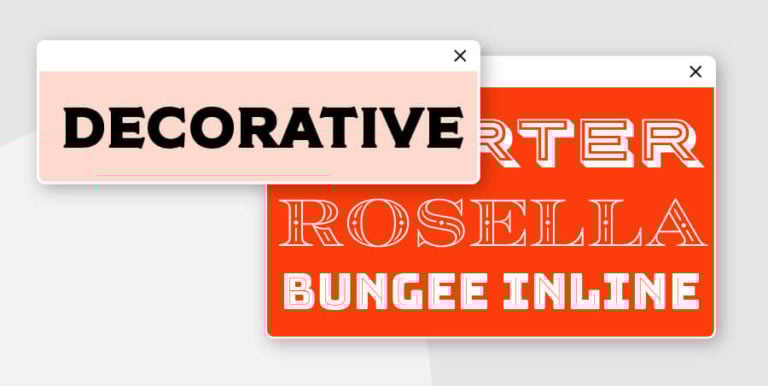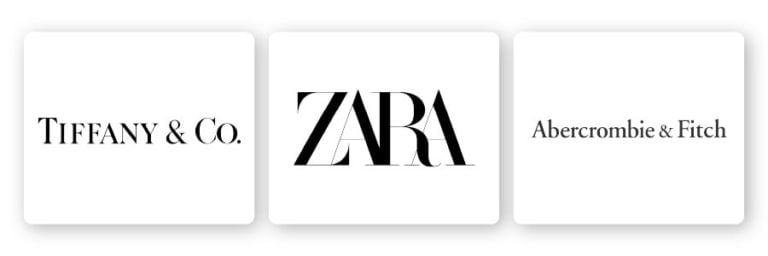
Wenn Sie ein Logo entwerfen wollen, ist die Wahl der richtigen Schriftart vergleichbar mit der Auswahl der Außenfarbe für Ihr Haus. Sie sollten genau die richtige aussuchen, denn das neue Erscheinungsbild gibt Ihrem Zuhause neue Frische und sagt Ihren Gästen viel über die Menschen, die darin wohnen. Abblätternde Farbe zeugt von einem vernachlässigtem Zuhause; glänzende, lebendige Farben besagt, dass es sich um ein gut gepflegtes Heim handelt.
In der Weise, wie Farben Aussagen über Häuser machen, so werden Schriftarten dazu benutzt, um spezifische Reaktionen hervorzurufen und einzigartige gedankliche Assoziationen mit einer Marke herzustellen. Jede Schriftart hat ihre eigenen Vor- und Nachteile sowie psychologische Bedeutung.
Heutzutage sind Tausende von kostenlosen Schriftarten verfügbar, aber die meisten lassen sich in fünf weite Kategorien aufteilen. Jeder dieser Stile besitzt charakteristische Merkmale und wie der jeweilige eingesetzt bzw. gestaltet wird, spielt eine wichtige Rolle für dessen symbolische Bedeutung – was sich wiederum auf Ihr endgültiges Logodesign auswirkt.
Lesen Sie weiter, um mehr über jede Schriftart zu erfahren, und finden Sie heraus, welcher Stil die richtige Auswirkung auf Ihr Logo hat.
Die verschiedenen Typen von Schriftarten, und wann man sie verwendet
Serifen-Fonts
Dies sind die ältesten Schriftarten, von denen die ersten Beispiele bereits im späten 15. Jahrhundert auftauchen. Das Wort „Serife“ bezieht sich auf die kleinen Füße, mit denen die einzelnen Buchstaben oben und unten ausgestattet sind. Diese winzigen Verzierungen sind auf die künstlerischen Pinselstriche zurückzuführen, die den Buchstaben als dekoratives Element hinzugefügt wurden.
Serif-Fonts lassen sich noch weiter in verschiedene Unterkategorien (Alter Stil, Klassik, Neo-Klassisch, Übergang, Clarendon etc.) unterteilen. Heutzutage gehören die Serifen-Fonts zu den beliebtesten gebräuchlichen Schrifttypen, wobei Stile wie „Times New Roman“ überall in Büchern, Dokumenten und sogar in einigen Logos anzutreffen sind.
Diese Schriftart zeichnet sich durch ein eher konservatives Design und (abgesehen einiger der vielen Unterklassen) durch das Vorhandensein von Serifen am oberen und unteren Buchstabenende aus.
Marken, die Serifen verwenden: Zara, Tiffany & Co und Abercrombie & Fitch.
Die Psychologie der Serifen-Fonts: Serifen-Fonts sind beliebt bei Unternehmen, die versuchen, sich als eine elegante, niveauvolle Marke zu präsentieren. Logos mit diesen Schrifttypen stehen für Tradition, Seriosität und Zuverlässigkeit.
Darüber hinaus unterstützen Serifen Unternehmen dabei, etablierter zu erscheinen, und sind ideal zur Vermittlung einer auf Autorität und traditioneller Größe basierenden Identität. Organisationen im akademischen, redaktionellen und finanziellen Bereich bevorzugen Serif-Fonts dank dem konservativen und seriösen Erscheinungsbild.
Serifenlose Fonts
Serifenlose Schriftarten verzichten für einen gradlinigeren, moderneren Ansatz auf die Verzierungen der zuvor genannten und dieser Kontrast macht sie zu einer guten Ergänzung für Serif-Fonts. Sie reichen zurück bis ins 19. Jahrhundert und waren in den 1920er und 30er Jahren äußerst beliebt. In der Mitte des 20. Jahrhunderts entwickelten deutsche Designer mit der Schaffung des beliebten Helvetica-Designs den Schrifttyp noch weiter.
Diese Schriftarten zeichnen sich durch klare, gerade Linien aus. Sie besitzen keine Verzierungen und legen die Betonung zu Gunsten eines skalierbareren Erscheinungsbilds auf Lesbarkeit und Einfachheit. Serifenlose Schriftarten lassen sich ebenfalls in mehrere stilistische Unterkategorien wie u. a. Grotesque, Quadratisch, Geometrisch und Humanistisch aufteilen.
Marken, die serifenlose Fonts verwenden: LinkedIn, Calvin Klein und The Guardian.
Die Psychologie der serifenlosen Fonts: Diese Fonttypen bieten ein gradliniges Erscheinungsbild ohne jeglichen Schnickschnack. Sie betonen Klarheit mit einem zukunftsorientierten Ansatz. – Sie können aber auch ausdrucksstark sein und dank ihres geschliffenen und effizienten Designs als Blickfang dienen. Unternehmen, die sich für diese Schriftfamilie entscheiden, setzen Priorität auf ein Gefühl von Feingefühl und Ehrlichkeit, bei dem Schnörkel oder Flair überflüssig sind.
Slab-Serifen- bzw. Egyptienne-Fonts
Slab-Serifen sind eine Variante der klassischen Serifen-Typografie und traten im 19. Jahrhundert erstmals in Erscheinung. Diese Schrifttypen sind aussagekräftig und betonen die Abkehr von klassischen Varianten. Die für Serifen-Fonts typischen Füße sind größer und blockähnlicher (d. h. sie sehen wie „Platten“ aus).
Kennzeichen dieser Schriftarten ist ihr solider und ausdrucksstarker Ansatz. Man findet sie häufiger in Verbindung mit modernen als klassischen Marken. Diese Fonts können entweder abgerundet oder eckig sein, wobei einige Schreibmaschinenstilen sehr ähnlich sind.
Marken, die Slab-Serif verwenden: Sony, Honda und Volvo.
Die Psychologie der Slab-Serif-Fonts: Bei diesen Schriftarten geht es vor allem um ein lautes, ausdrucksstarkes Image. Sie vermitteln ein Gefühl von Vertrauen, Zuverlässigkeit und kreativem Gedankengut dank ihrer starken Linien und weniger feinen Serifen. Marken, die es darauf anlegen, große Aufmerksamkeit zu erregen oder hervorzuheben, wie innovativ ihre Ideen und Produkte sind, wählen Slab-Serif-Fonts, da sie helfen können, einen Eindruck von Wichtigkeit und Bedarf zu vermitteln.
Die Wahl des geeigneten Fonts ist ein entscheidender Aspekt in Hinblick auf jede Markenidentität. Die richtige verleiht Ihrer Marke ein weiteres symbolisches Plus, das dazu beiträgt, die Werte und Ziele Ihres Unternehmens besser zu kommunizieren.
Überlegen Sie auf jeden Fall, wie jede Schriftart und Fontstil Ihrem Markenimage zuträglich ist. Wenn Sie es schaffen, die richtige Mischung von Schriftarten und Designelementen zusammenzustellen, hat Ihre Marke die Möglichkeit, die Geschichte Ihres Unternehmens so wiederzugeben, wie sie erzählt werden sollte.